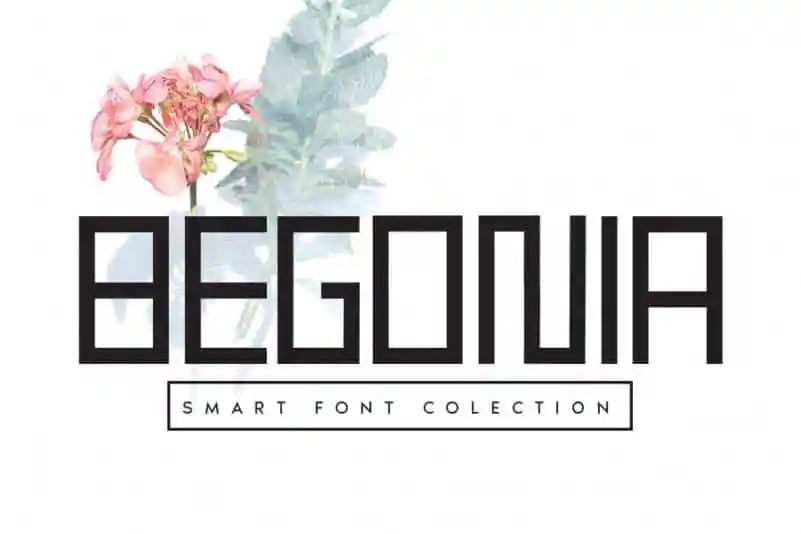
Begonia Display Font – Download Grátis
Begonia Display Font é uma fonte serif que traz um toque de desenho único para qualquer projeto impresso ou digital. Suas linhas grossas e curvas alegres podem adicionar um toque criativo e divertido às suas criações, seja para aplicativos móveis ou websites. Esta fonte foi criada pelo designer andikastudio, e é uma excelente escolha para quem procura uma opção diferente para dar vida ao design de seus projetos. Use Begonia Display Font para personalizar as letras de um logotipo, dar um charme especial às cartas pessoais ou até mesmo estilizar o texto dos anúncios online, tornando-as mais atraentes e memoráveis para seu público-alvo.